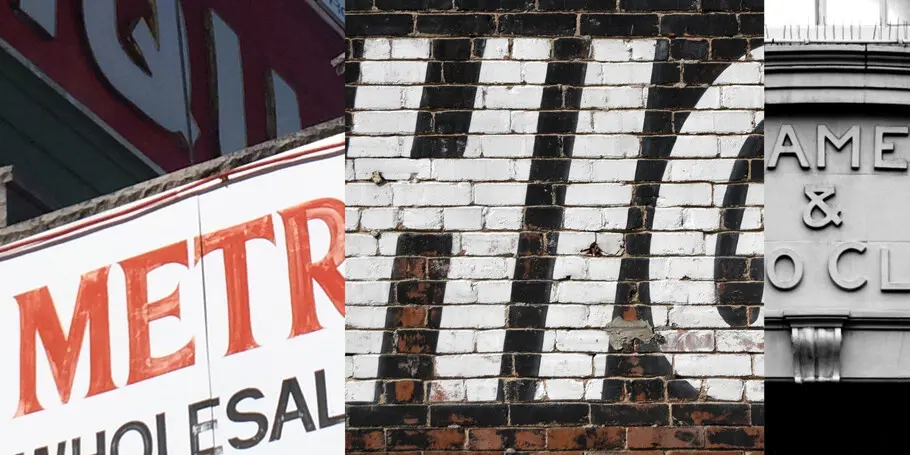
Boostez votre créativité : découvrez 8 sources d'inspiration à l'efficacité redoutable.
Comment atteindre cet état de flow créatif pour donner du caractère votre projet ?
En tant que créatif moderne, vous pouvez facilement vous laisser séduire par les tendances et nouveautés. Mais avant de vous lancer dans le processus d’idéation, il est également important d’analyser et de remplir les contraintes du brief sur lequel vous travaillez. Cela étant dit, commençons par le commencement : comment atteindre cet état de flow créatif tant convoité pour donner du caractère à votre projet ?
Afin d’enrichir vos idées, vous avez probablement déjà l’habitude de naviguer sur Behance ou Pinterest. Voici quelques (autres) grandes sources d’inspiration en matière de design :
1. The Brand Identity et It’s Nice That – Ressources de design mondialement reconnues, ces deux plateformes ont pour but de défendre la créativité (jetez un œil à la mission de It’s Nice That). Le contenu proposé est toujours de haute qualité. On y trouve de beaux exemples de design graphique et de travail créatif.
2. Pangram Paper – Le studio de création typographique Pangram est basé à Montréal au Canada. Il produit une plateforme éditoriale « expérimentale » qui mêle actualités sur le design, sorties de nouvelles typographies et interviews de designers.
3. Fresh Fonts newsletter – Cette newsletter indépendante et payante fait le point sur tout ce qui se passe dans le monde de la typographie. Le meilleur ? Les abonnés reçoivent une famille de polices gratuite chaque mois. Non seulement vous soutenez les designers typographiques à travers votre abonnement, mais vous recevez également un kit de polices gratuites dans votre boîte de réception tous les mois.
4. Adobe Live – En collaboration avec Behance, Adobe propose des sessions en ligne avec des créatifs, chaque semaine. Organisées en France, en Allemagne, au Royaume-Uni et aux États-Unis, elles constituent une ressource fantastique. Plongés dans l’univers des créatifs, vous êtes amenés à découvrir leurs astuces sur différents aspects pratiques de cet univers.
5. Weekly Typographic podcast – Ce podcast hebdomadaire, créé par The League of Moveable Type, en est à sa troisième saison. Au programme, des conversations approfondies sur la communauté du design et de la typographie, notamment les expositions, les nouvelles sorties et des interviews de designers.
6. Instagram – Surnommé « le LinkedIn des créatifs », ce réseau fait déjà probablement partie de vos applications pour partager ou trouver l’inspiration. L’idée ici consiste surtout à travailler votre feed, de manière à en faire un outil d’inspiration complet. Organisez vos feeds afin de stimuler votre inspiration, tout en évitant de tomber dans les abysses du scrolling sans fin. Sauvegardez le contenu qui vous semble pertinent ou qui attire votre attention.
7. Les livres – Se constituer une bibliothèque polyvalente à la maison peut prendre des années, mais l’effort en vaut la peine lorsque vous avez besoin de prendre du recul et de revenir à l’aspect matériel des choses. Rien ne remplace la vivacité du texte imprimé dans les livres, ni le contexte historique ; de précieux éléments qui peuvent se perdre dans le flot incessant de contenu en ligne.
8. Le « monde réel » – Lors d’un travail créatif, on peut très facilement perdre le contact au profit des écrans. N’oubliez pas le monde physique qui vous entoure. Observez les pancartes rédigées à la main, les fleurs multicolores en pleine nature ou les modèles de voitures aux formes particulières. Une fois que vous avez entraîné votre cerveau à filtrer ce que vous trouvez inspirant, le processus deviendra automatique.
Certaines campagnes récentes, réputées pour leur utilisation efficace de la typographie et de la technologie, peuvent constituer des sources d’inspiration supplémentaires.
Le rebranding de l’Orchestre symphonique de San Francisco par COLLINS – L’agence COLLINS et la fonderie suisse Dinamo Typefaces se sont associées dans le cadre de ce projet pour l’Orchestre symphonique de San Francisco. Ensemble, elles ont démontré la puissance de la technologie des polices variables, lorsqu’elle est utilisée pour renforcer la voix et le contenu de la marque. Les formes des caractères sont percutantes et contemporaines, réactives et variables. Chaque lettre se transforme avec le son de la musique. Ce rebranding remarquable montre comment la technologie variable peut faire avancer un concept design, en assurant une certaine cohérence.
M&M’S et son rebranding par JKR – La célèbre marque de bonbons au chocolat a fait peau neuve, grâce à l’​​agence JKR et Monotype. L’objectif : créer un monde où chacun se sent à sa place. Dans le cadre de ce rebranding, l’identité visuelle et les personnalités des personnages M&M’S ont été actualisées. Le ton de voix est plus inclusif et accueillant. Une police de caractères variable et personnalisée appelée All Together attire l’attention – c’est une police qui évoque divers concepts tels que la notion de famille, la chaleur humaine et la communication.
Pour les Jeux Olympiques et Paralympiques de Paris 2024 : une typographie sur mesure par Julie Soudanne de l’agence Elliott Amblard – Cette police personnalisée conçue pour Paris 2024 fait écho aux derniers Jeux ayant eu lieu à Paris, en 1924. Son style, teinté de courbes et d’inclinaisons, est emblématique de l’Art déco, synonyme d’élégance à la française. La police sur mesure reste pourtant résolument contemporaine et admet une version variable, conçue spécialement pour s’adapter à tous les environnements.